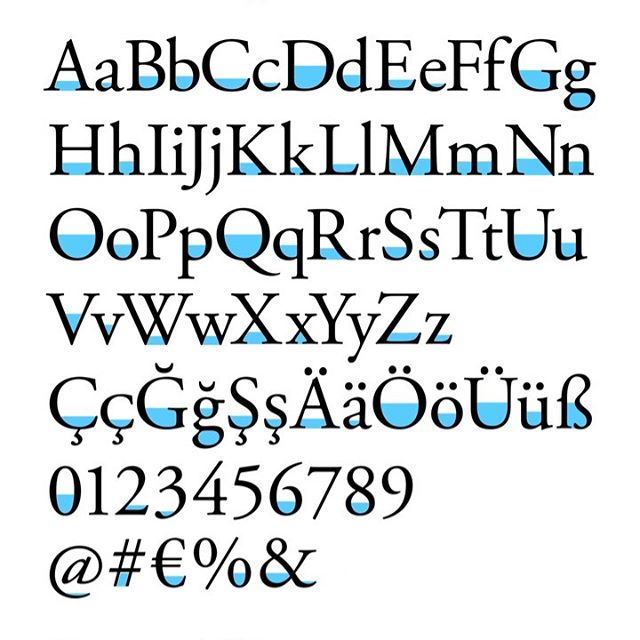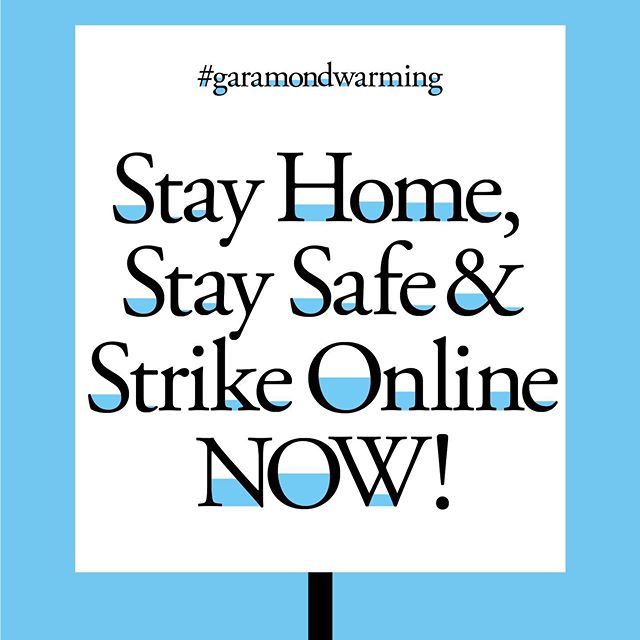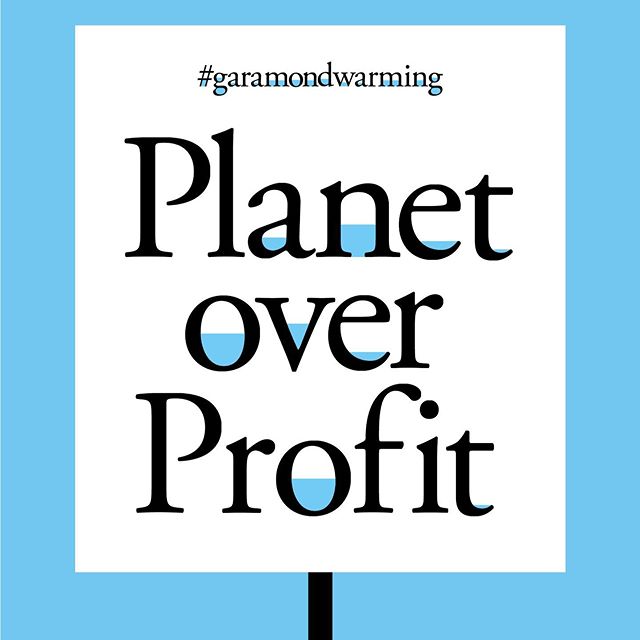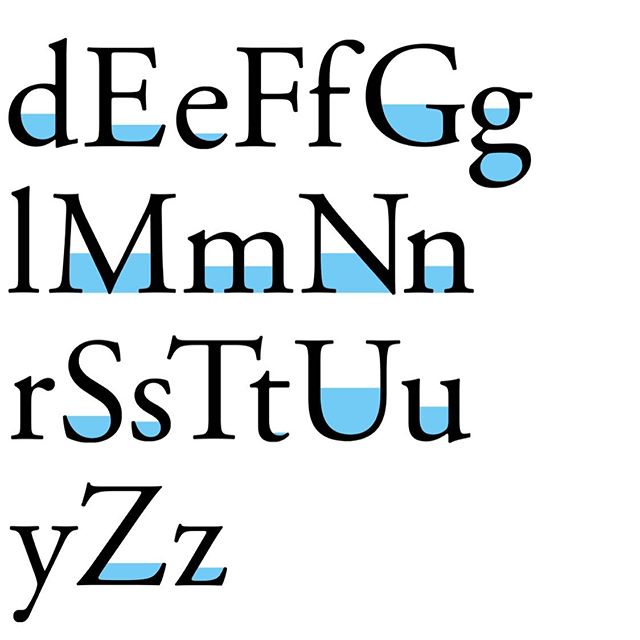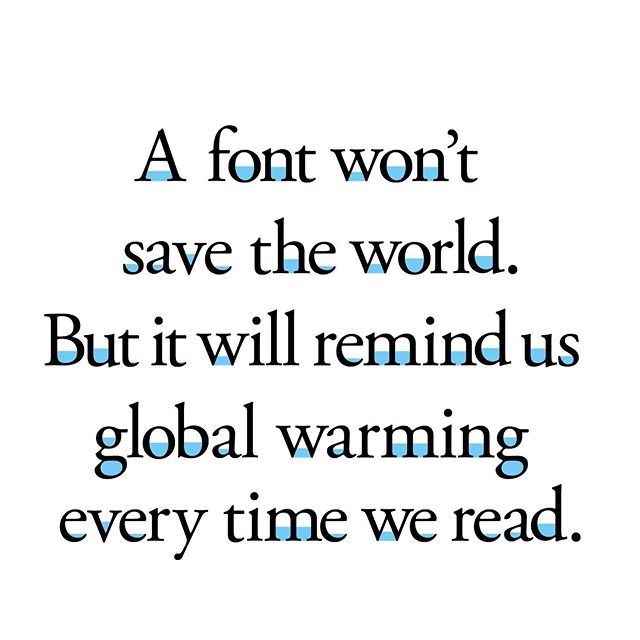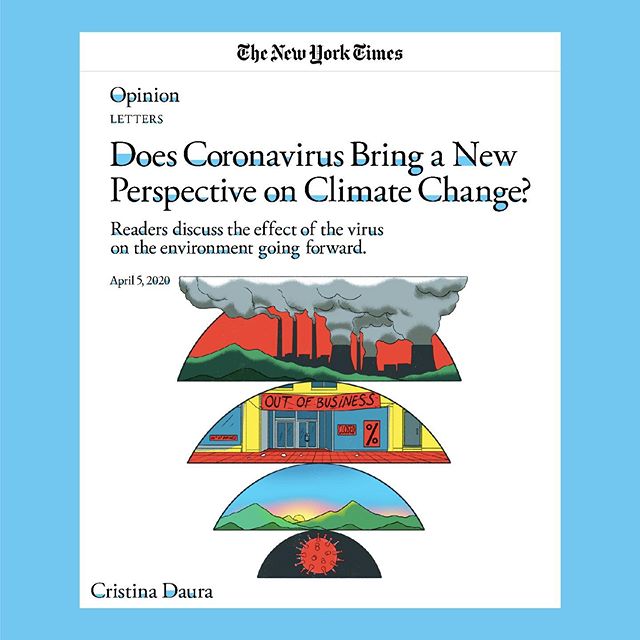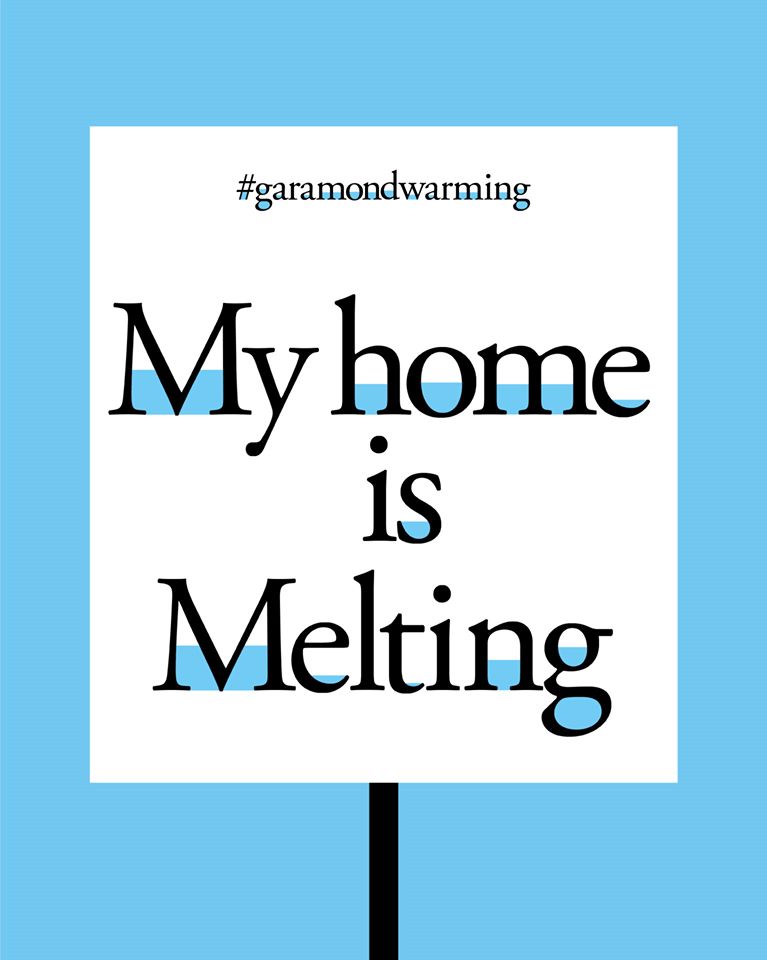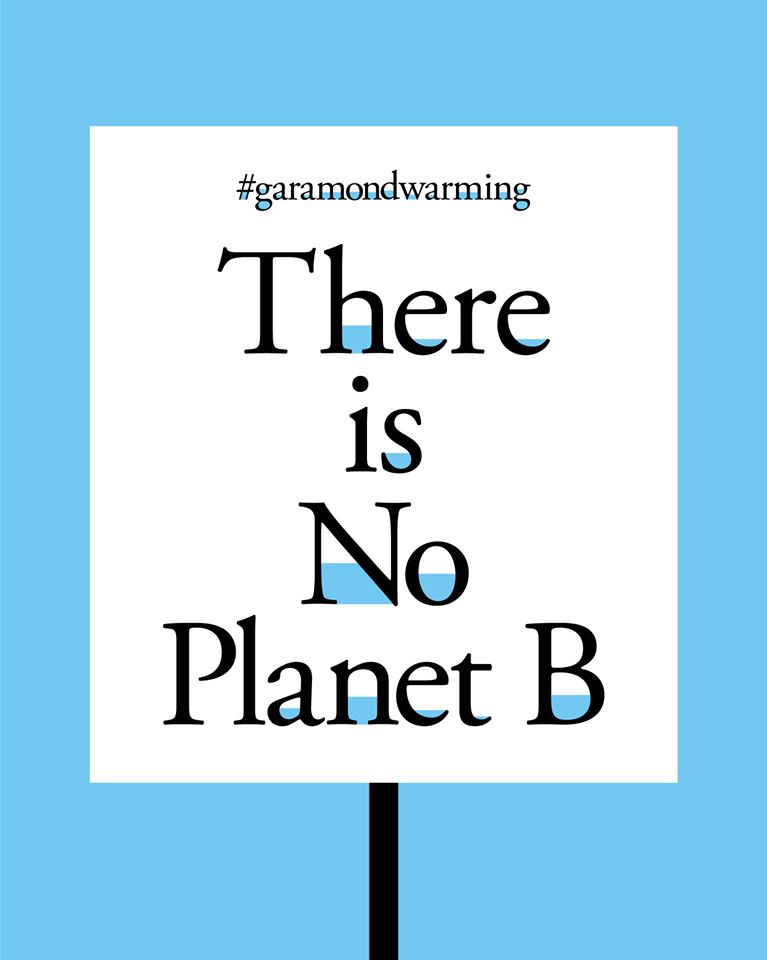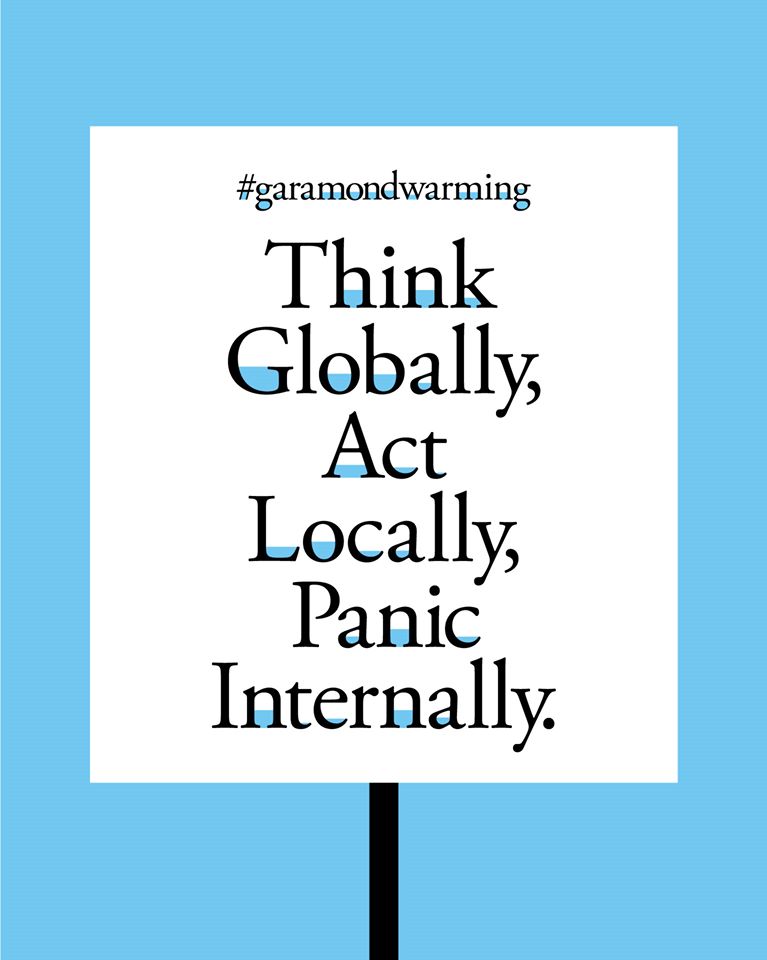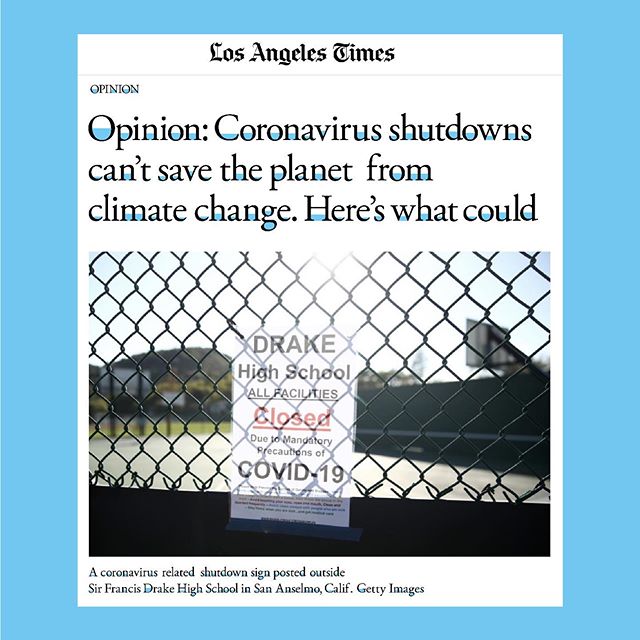
Khi đại dịch coronavirus chiếm lĩnh hầu hết các kênh tin tức, một nhà sáng tạo người Đức có một hy vọng biến biến khí hậu thành điều được quan tâm hơn bằng cách thiết kế một phông chữ thông minh.
Yiğit Karagöz, giám đốc nghệ thuật cao cấp tại Scholz & Friends ở Hamburg, đã phát hành một phông chữ có thể tải xuống miễn phí trong tuần này có tên là Garhua Warming, một khuynh hướng về phong cách phông chữ cổ điển mà theo nghĩa đen là mô tả từng nhân vật bị ngập lụt. Thiết kế có các chữ cái với nhiều mức độ tô màu khác nhau trong khẩu độ của chúng. Thiết kế typography cho các khoảng trống của ký tự được bao bọc một phần hoặc hoàn toàn bởi các mảng màu và trông chúng như đang bị ngập lụt. (ví dụ: ở giữa chữ O hoặc hoặc U).
Karagöz cho biết anh đã sử dụng kiểu chữ Garhua, nguồn gốc xuất hiện từ những lần in ấn đầu tiên của đầu thế kỷ 16, như một hình thức phát triển thiết kế. Sau đó, anh đã cố gắng tìm các phương pháp tinh chỉnh để cho nó có cảm giác nhưng đang bị chết đuối.
Anh ấy hy vọng rằng mọi người sẽ bắt đầu tải xuống và sử dụng phông chữ của riêng họ như một cách để truyền bá thông điệp hơn nữa. Để làm được điều đó, anh ấy đã giới thiệu nó trên Instagram với những tựa báo được thể hiện bằng font chữ này.
Karagöz nói rằng sẽ tốt hơn khi nó lan truyền rất nhiều vì mọi người đều có thể sử dụng nó khá dễ dàng. Sau đó, nó sẽ phục vụ như một lời nhắc nhở nhỏ cho mọi người rằng hàng triệu người sẽ bị ảnh hưởng bởi vấn đề này.
Đây không phải là lần đầu tiên Karagöz tìm cách gây chú ý đến biến đổi khí hậu thông qua kiểu chữ. Trước đó, anh đã phát hành một phông chữ khi còn làm tại TBWA \ Istanbul, được tạo kiểu giống với chữ ký của các nhà lãnh đạo thế giới khác nhau cho Hội nghị thượng đỉnh G20 2018.